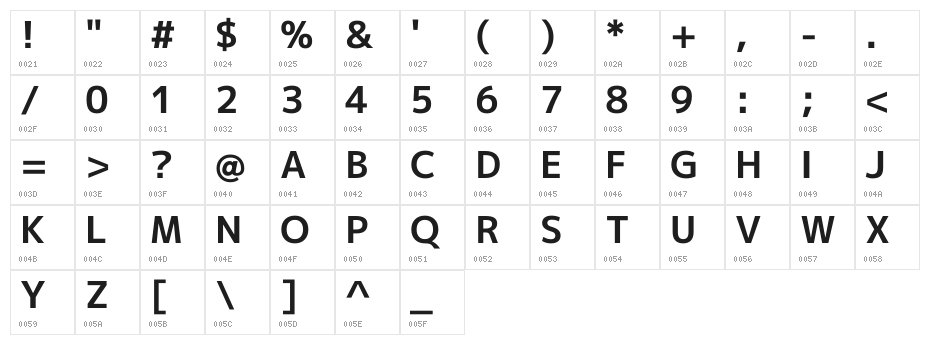
M+ 2p bold Font
| Caso d'uso | Headlines, Logos, Digital interfaces |
| Progetti proposti | Ideal for branding, advertising, headlines, and digital interfaces where clarity and impact are essential. |